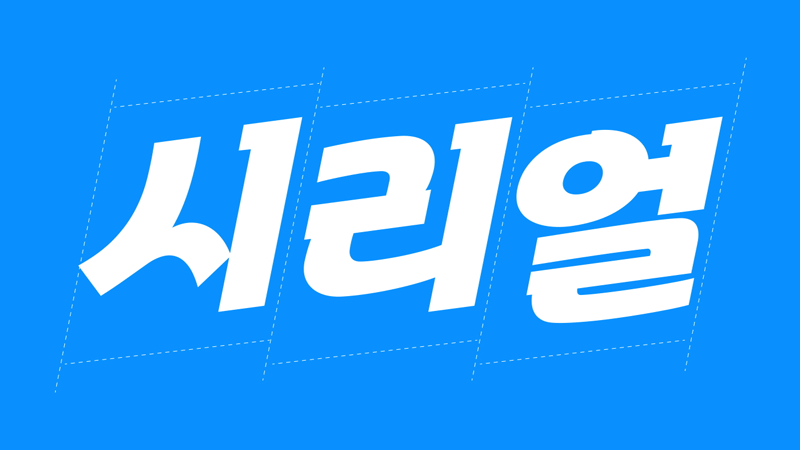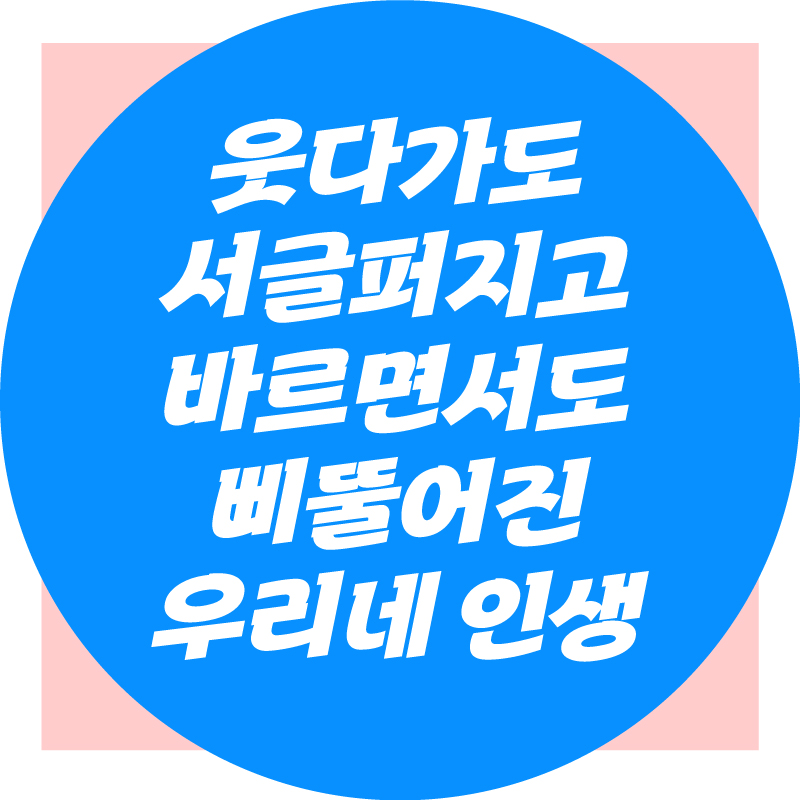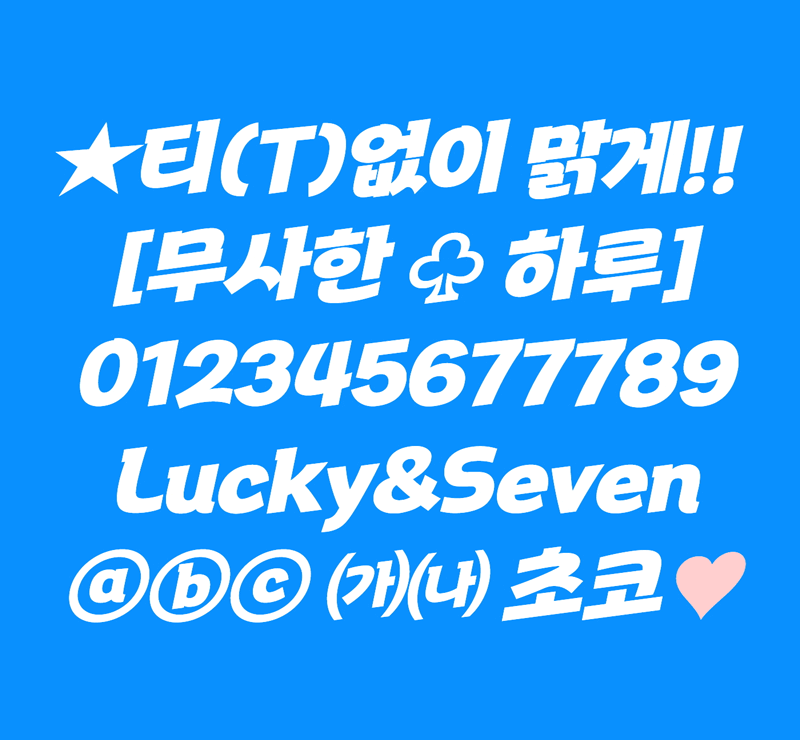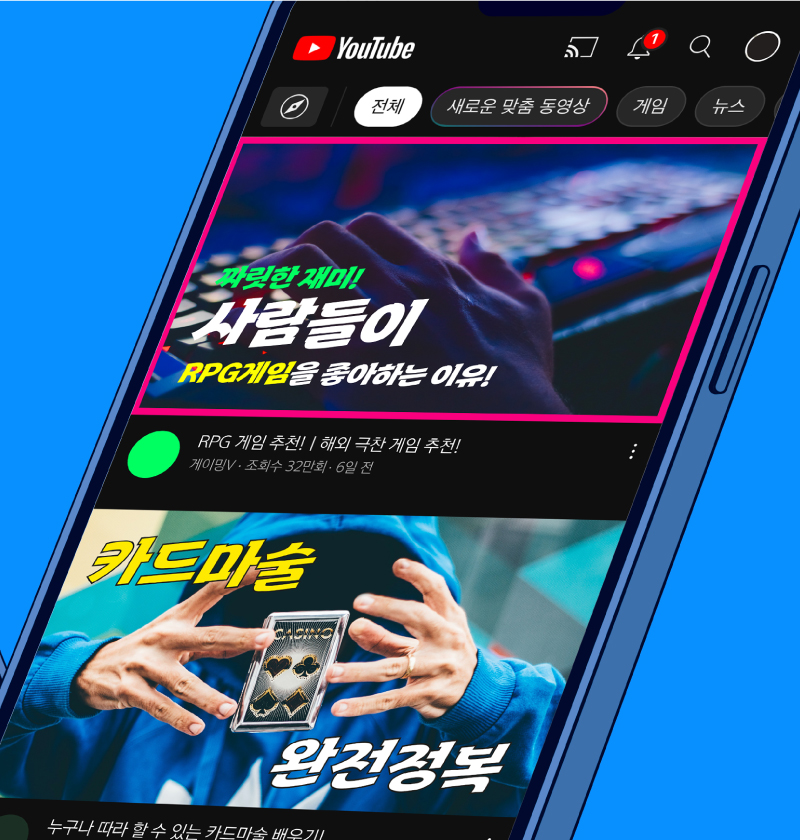
RixParan
1 Style - Regular과감한 기울기와 빠른 획순이 역동적인 느낌을 주는 서체입니다.
굵기가 두껍지만 부드럽고 자유로운 손글씨 디자인을 접목해 캐주얼한 인상을 줍니다.
획의 대비가 적은 슬랩 세리프로 주목성을 높여 다양한 매체에 활용할 수 있습니다.